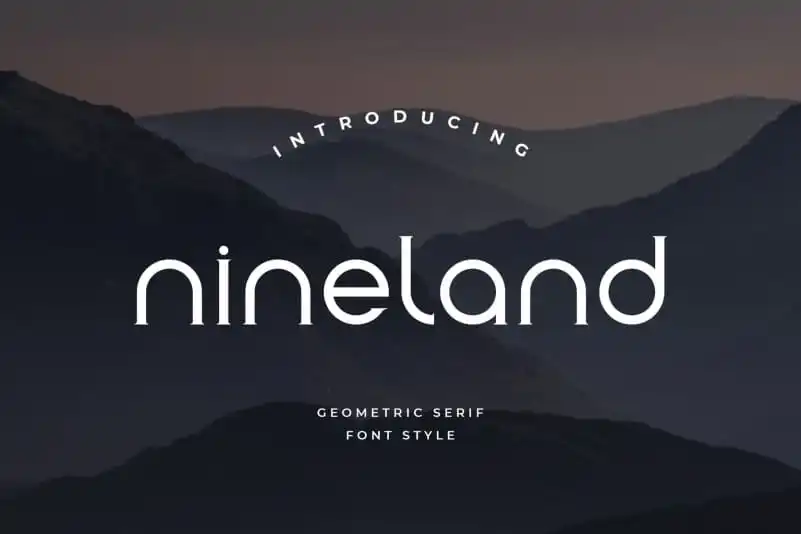
Introduzimos a Nineland Display Font, uma fonte tipo-display única e interessante que traz um toque moderno à sua identidade visual. Com suporte para caracteres multilíngue, essa fonte versátil é perfeita tanto para projetos de branding quanto para produtos como rótulos de embalagens elegantes, logotipos sofisticados e até mesmo camisetas e posters chamativos. A Nineland Display é uma família serifada com um aspecto casual mas sempre elegante. Suas letras trazem formas redondas e geométricas nas quatro direções para uma aparência neat e de qualidade, garantindo equilíbrio visual em qualquer aplicação. Com seus caracteres entre maiúsculo e minúsculo, números e pontuação complementar, a Nineland Display está sempre pronta para ajudá-lo a transformar ideias inspiradoras em projetos poderosos. Descubra o encanto de uma fonte que combina sofisticação com modernidade, perfeita tanto para criar rótulos elegantes quanto logotipos impressionantes. Tornando sua próxima criação ainda mais inspiradora e atraente!